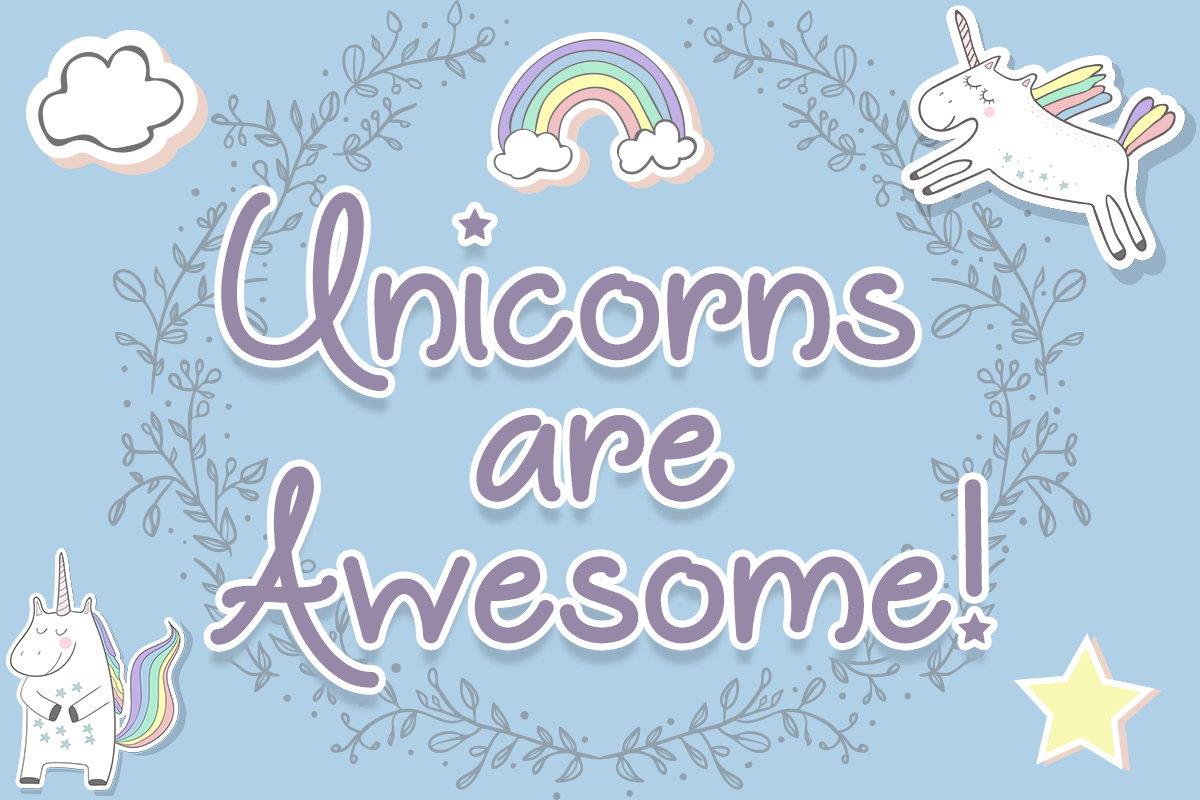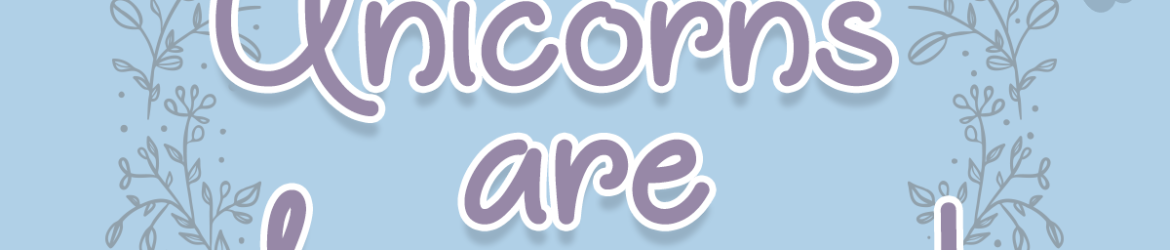
A fonte “Unicorns are Awesome” é uma escolha perfeita para aqueles que buscam algo mais jovem e lúdico no design tipográfico. Misti’s Fonts introduz esse originalmente handwritten font, ideal tanto para adicionar um toque criativo a qualquer projeto de design como para personalizar mensagens pessoais com frases preferidas ou textos favoritos dos usuários em suas imagens. Com uma característica única e divertida que encanta por sua forma infantil e icônica, esta fonte traz consigo uma atmosfera de brincadeira e inocência. Seja para adicionar um toque alegre a seu logotipo, personalizar as mensagens dos seus materiais de marketing ou simplesmente criar um design mais divertido e emocionante, “Unicorns are Awesome” oferece opções variadas que você pode misturar e combinar conforme necessário. Para designers digitais apaixonados por unicórnios e outras formas de arte visual, esta fonte é uma ótima maneira de expressar seus sentimentos ou ideias em um formato único. Com “Unicorns are Awesome”, seja qual for o seu projeto, sua criatividade ganha um novo estilo e identidade única.
Designer: Misti’s Fonts